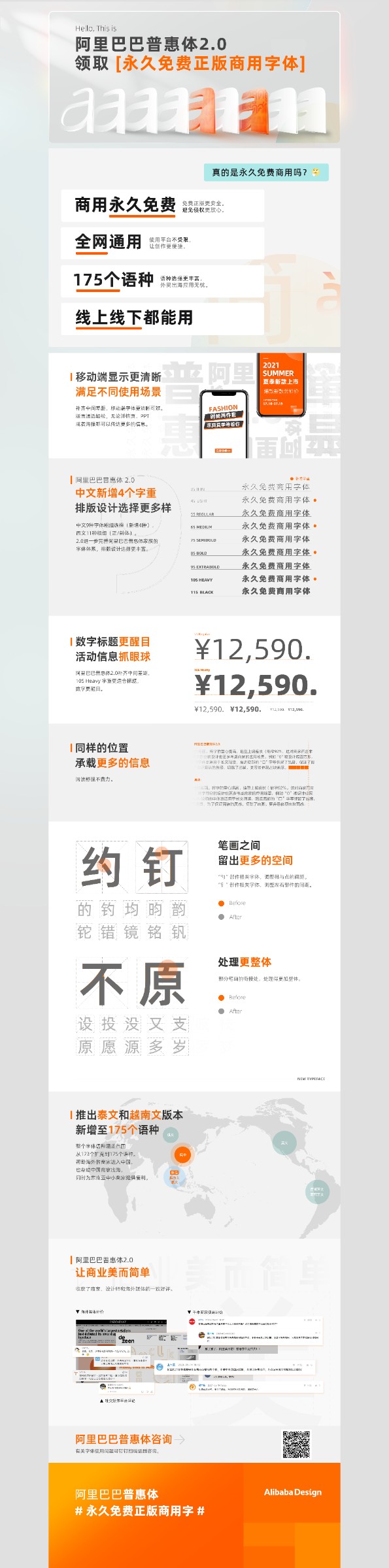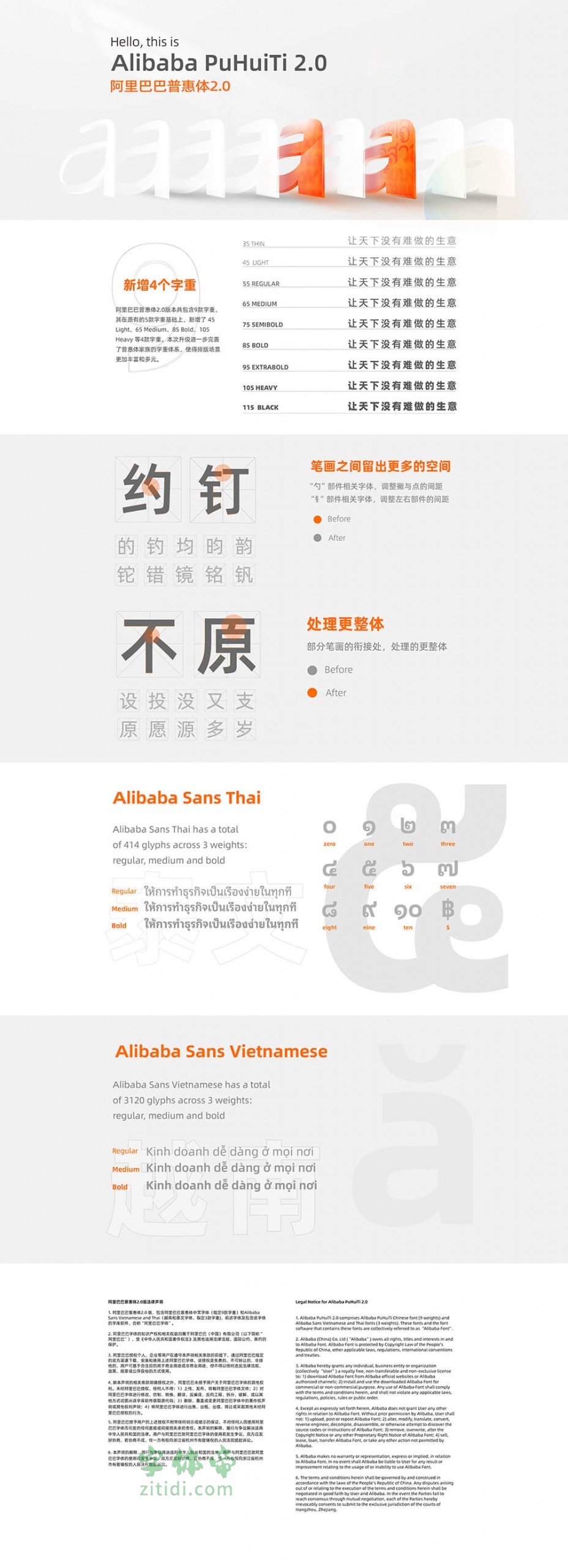
阿里巴巴于4月27日在UCAN 2019 设计大会上,率先向全社会发布了一款字体「阿里巴巴普惠体」,希望能够让阿里巴巴的普惠精神,让整个生态的设计师、合作伙伴因为我们平台的赋能,真正得到实惠。
这是一款由中国企业首次发布的可面向全场景使用的免费商用正文字体。以「普惠」之名诞生,这也意味着这款字体肩负着比一般企业品牌字更重要的使命──它还将开放商业授权给所有个人和商家,让更多用户可以免费使用这款阿里巴巴字体,以普惠设计赋能商家生态,实现阿里巴巴设计「让商业美而简单」的愿景。
青云表示,「20 岁的阿里正全速奔跑在全球化的轨道上,我们迫切需要一款统一的官方字体来构建阿里巴巴品牌的一致性和完整性,从而让大家更好地认识阿里巴巴,更懂我们的业务。」
随着 「 阿里巴巴普惠体 」 的发布,中国的可能免费商用的黑体字又增添一员,这标志着中国的设计行业正在朝着更好的方向迈进。现在可以免费商用并且支持多国语言的黑体字包括 「 思源黑体 」 、 「 OPPO Sans品牌字体 」等 。现在期待小米的兰亭黑体也可以加入免费商用行列。
这一次可免费商用的阿里普惠体共收录 116,895 个全形汉字(含 5 个字重),西文 Alibaba Sans 共 7,205 个拉丁字母(2 种风格、共 11 个字重),覆盖 172 个语种(覆盖大部分欧语国家),并可以满足阿里巴巴集团及其经济体公司在全球化业务下的多个应用场景需求。
据阿里巴巴定制字体项目负责人、阿里巴巴集团品牌高级创意设计专家羿光介绍,从去年 6 月至今,整套阿里巴巴普惠体的设计历时 10 个月,「不仅要包含突显企业品牌个性的标题字,还要囊括更为实用的内文字,兼顾多个场景下的应用……这么大体量的字体设计并面向全场景开放授权免费商用,开创了中国企业造字的先河。」